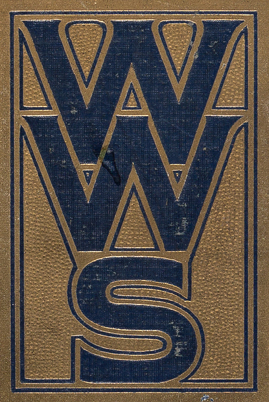
Wilhelm Woellmer’s Schriftgießerei
• Land: Deutschland
• Ort: Berlin
• Gegründet: 1854
• Status: nicht mehr aktiv
Wilhelm Woellmer gründete sein Unternehmen 1854 in Berlin als Handelsgeschäft für Buchdruckutensilien. Zehn Jahre später begann er auch auch mit der Herstellung und dem Vertrieb von Schriften.
Im Jahre 1883 wurde die Firma durch Siegmund Borchardt, den Teilhaber einer Papiergroßhandlung, übernommen. Im Jahr 1938 erschien die letzte eigenentwickelte Schrift und das Unternehmen wurde aufgelöst. Einige der Schriften gingen an die Gießereien Gebr. Klingspor, Genzsch & Heyse, Schriftguß KG und C. E. Weber über.